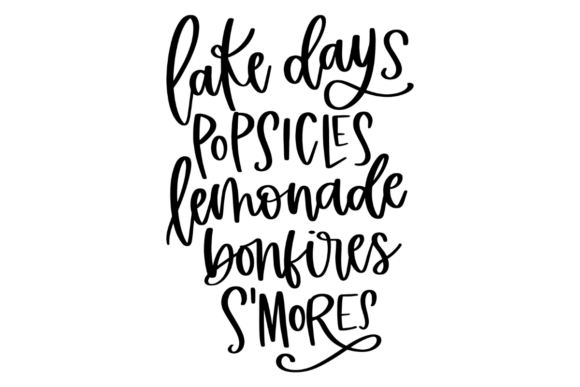
Summer Subway Art SVG
Việc tìm kiếm các thành phần thiết kế phù hợp có thể là một thách thức, nhưng Summer Subway Art SVG cung cấp một bộ sưu tập đặc biệt giúp nâng tầm công việc của bạn ngay lập tức.
Được chế tác với độ chính xác cao, Summer Subway Art SVG cung cấp các vector sạch, kiểu chữ mượt mà và giấy phép thương mại để bạn yên tâm.